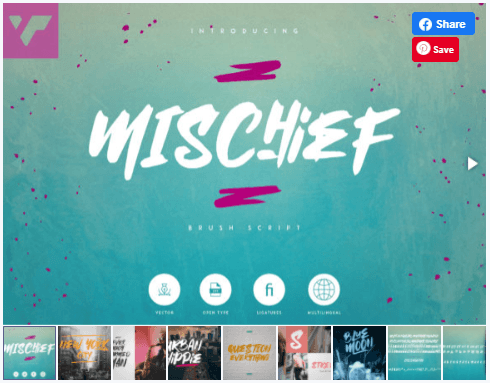
Mischief Font
Mischief - это забавный, городской, матовый дисплейный шрифт. Этот великолепный дисплейный шрифт превратит любую творческую идею в выдающуюся!